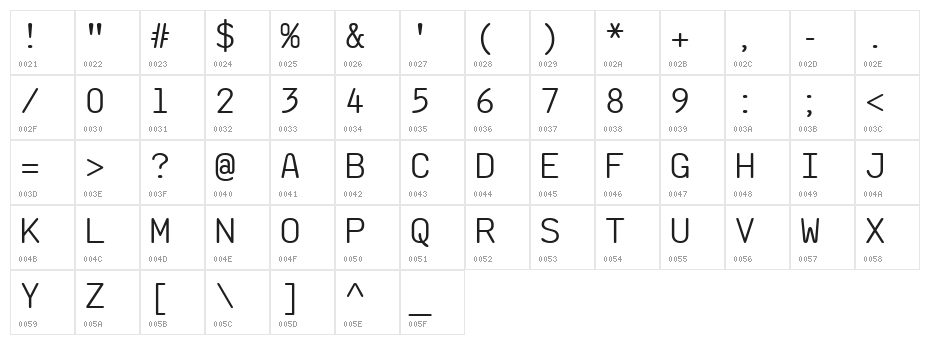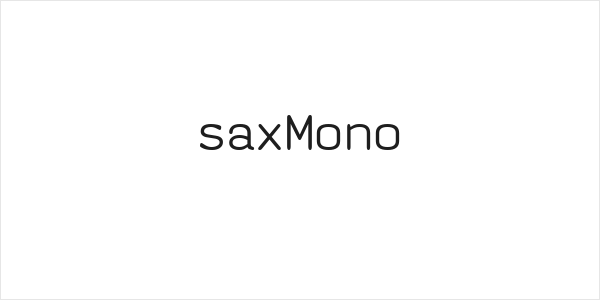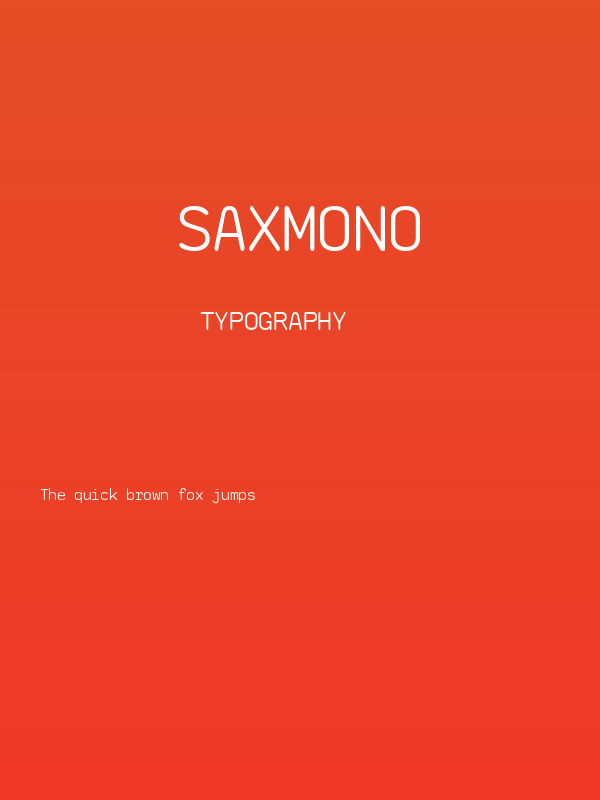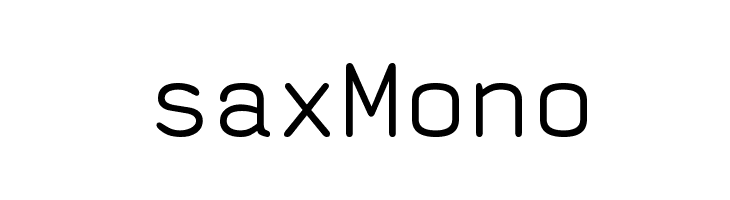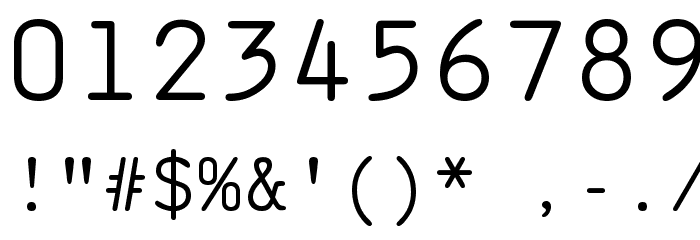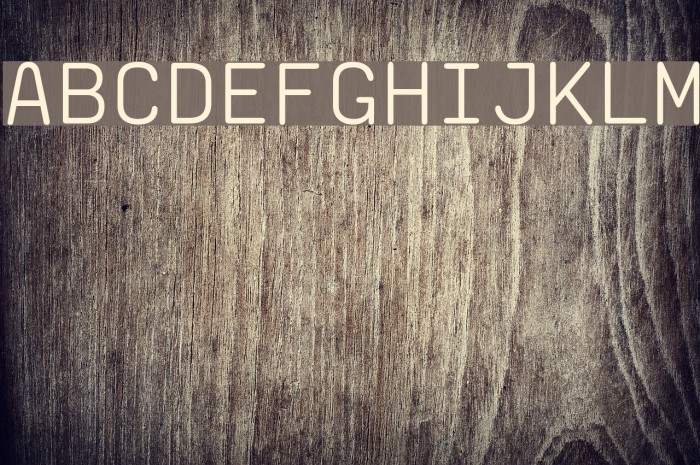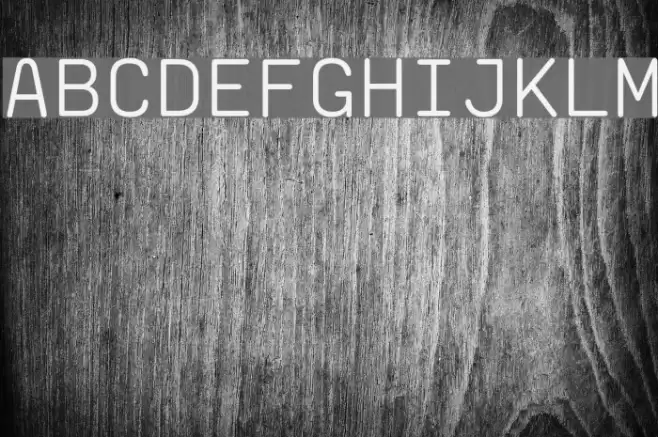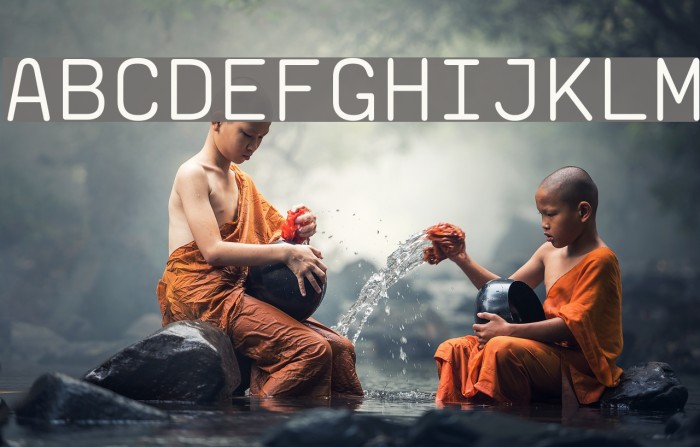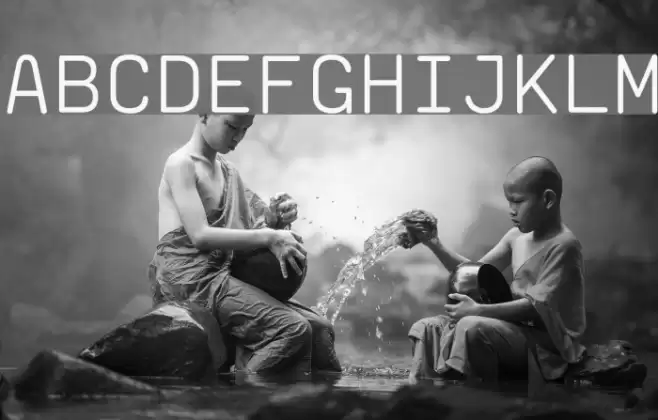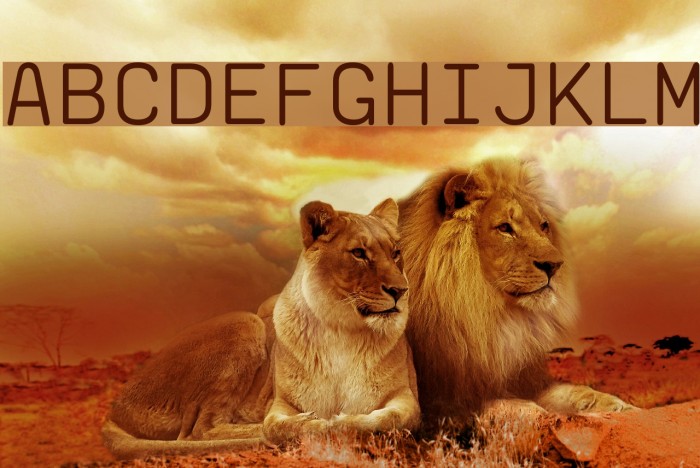
saxMono Font
| Espacement des caractères | Normal |
| Cas d'utilisation | Coding, Technical documentation, Minimalist design |
| Projets proposés | Ideal for coding environments, technical documentation, and minimalist design projects. |
| Est-hélice à pas fixe | Yes |